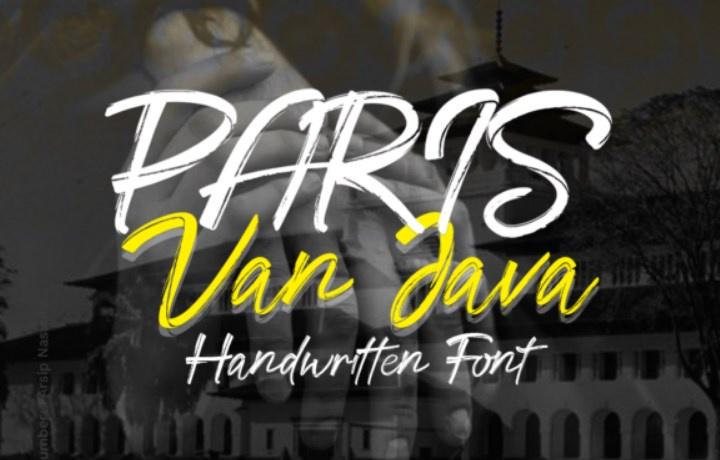
[creativefabrica] Java Font, 2022
Java — классный, аккуратный и отшлифованный рукописный шрифт. Он имеет уличную атмосферу и подойдет для ваших различных постеров, брендинга, дизайнов футболок и многого другого. используйте его уверенно!